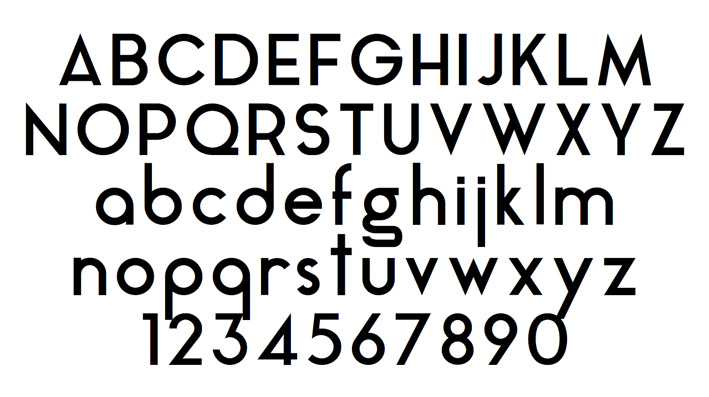
Tipografías gratuitas: Aqua Grotesque ha sido diseñada por Laura Pol <http://www.poldesigns.com> para la revista Neo2. Esta tipografía no se puede vender o regalar a terceros. El uso comercial de esta tipografía deberá incluir el siguiente texto legal: “La tipografía Aqua Grotesque ha sido diseñada por Laura Pol para la revista Neo2″.
Esta tipografía está inspirada en la tipografía geométrica de los años 40 y tiene reminiscencias de otras tipografías como Futura. Es perfecta para logotipos, titulares o posters.
Ha sido creada por Laura Pol, diseñadora y fundadora del estudio que lleva su mismo nombre.
Aqua Grotesque Typography designed by Laura Pol <http://www.poldesigns.com> for Neo2 magazine. This typeface can’t be sold or given to anybody. The commercial use of this typography should always incluye: “Aqua Grotesque typography designed by Laura Pol for Neo2 magazine”.
This typography is inspired by the geometric typography of the 40s and is reminiscent of other fonts such as Futura. It is perfect for logos, headlines or posters.
It was created by Laura Pol, designer and founder of the studio that bears her name.